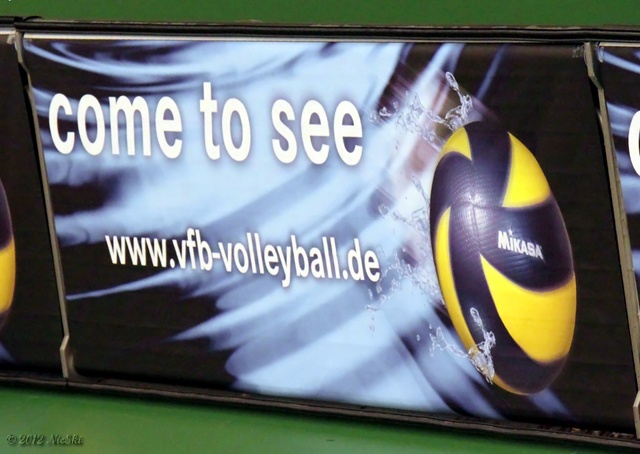
Suche nach dieser serifenlosen "Come to see" Schrift
Hallo zusammen, ich suche jetzt schon ne ganze Weile, bin aber noch nicht fündig geworden.
Erkennt von Euch jemand diese Schriftart?
Dem t nach zu schließen würde ich Nimbus Sans sagen … wobei das s dann ein klein wenig zu schmal ist … ein "Folienschnitzer-Helvetica-Derivat" wahrscheinlich.
Entzerrt sieht es so aus:
Die Punkte in der URL - darauf habe ich gar nicht geachtet.